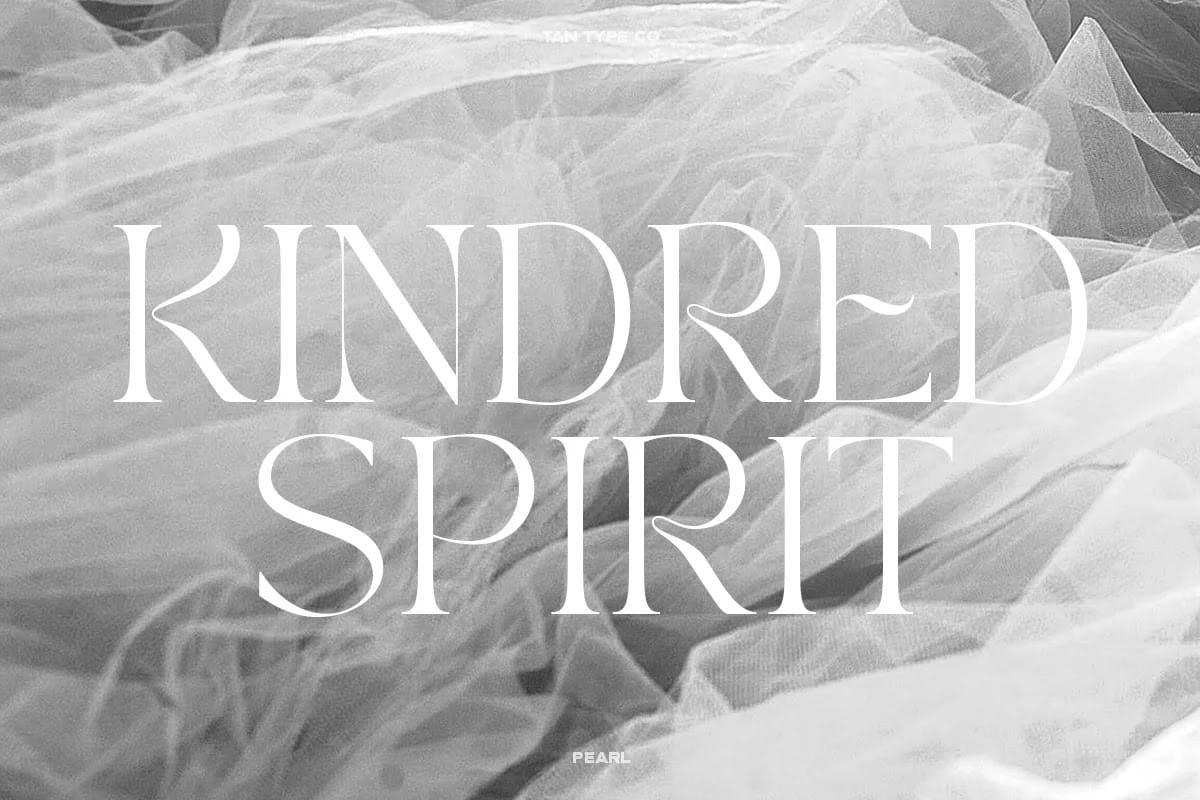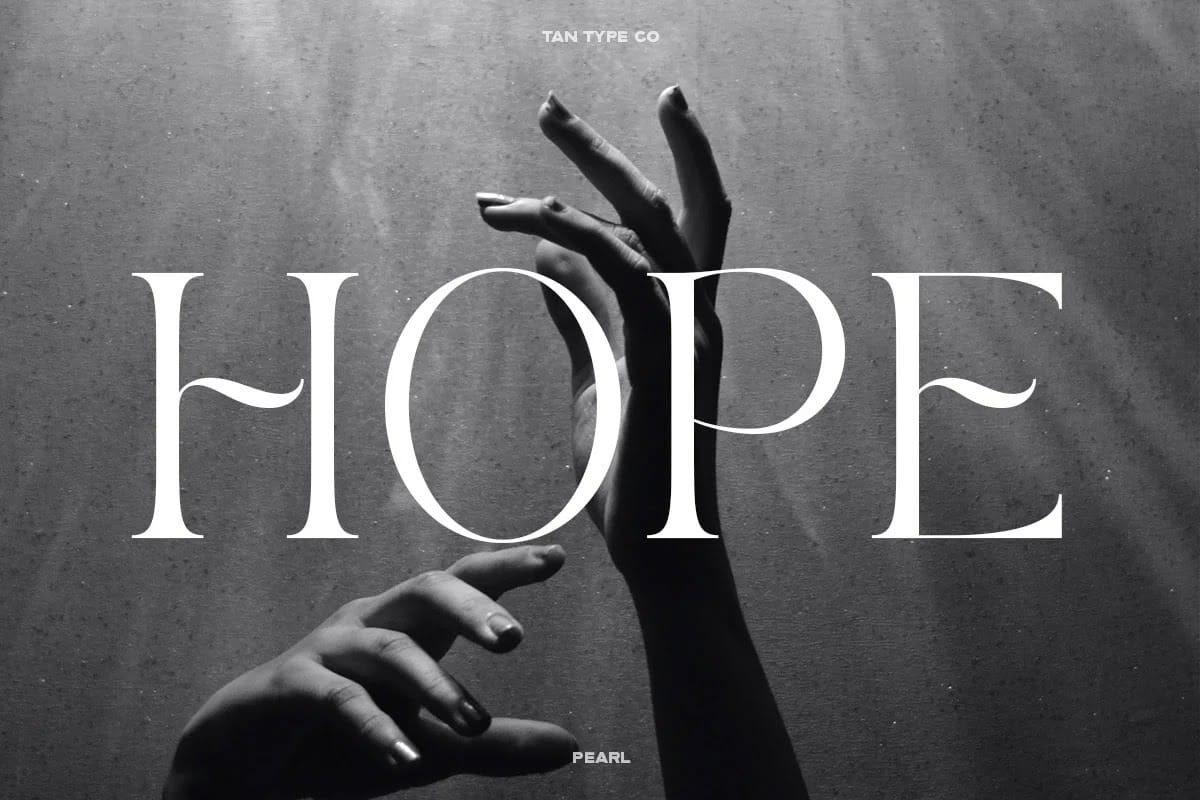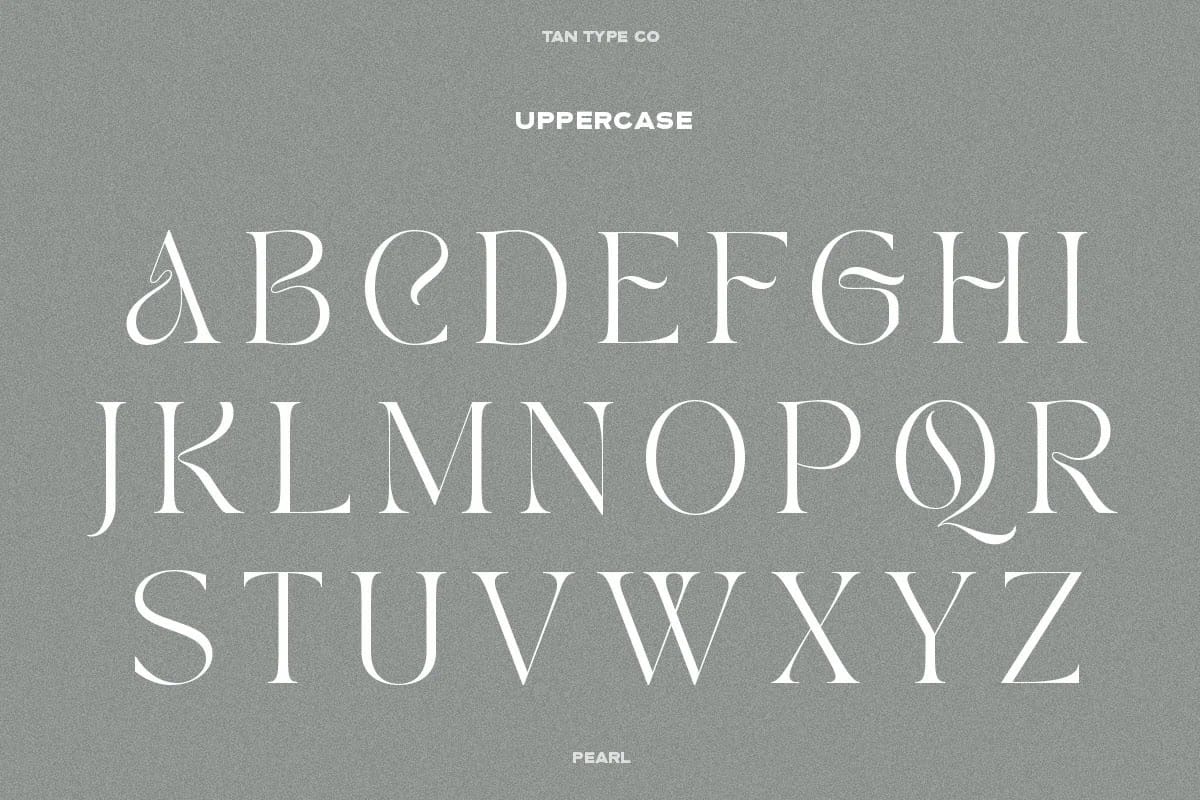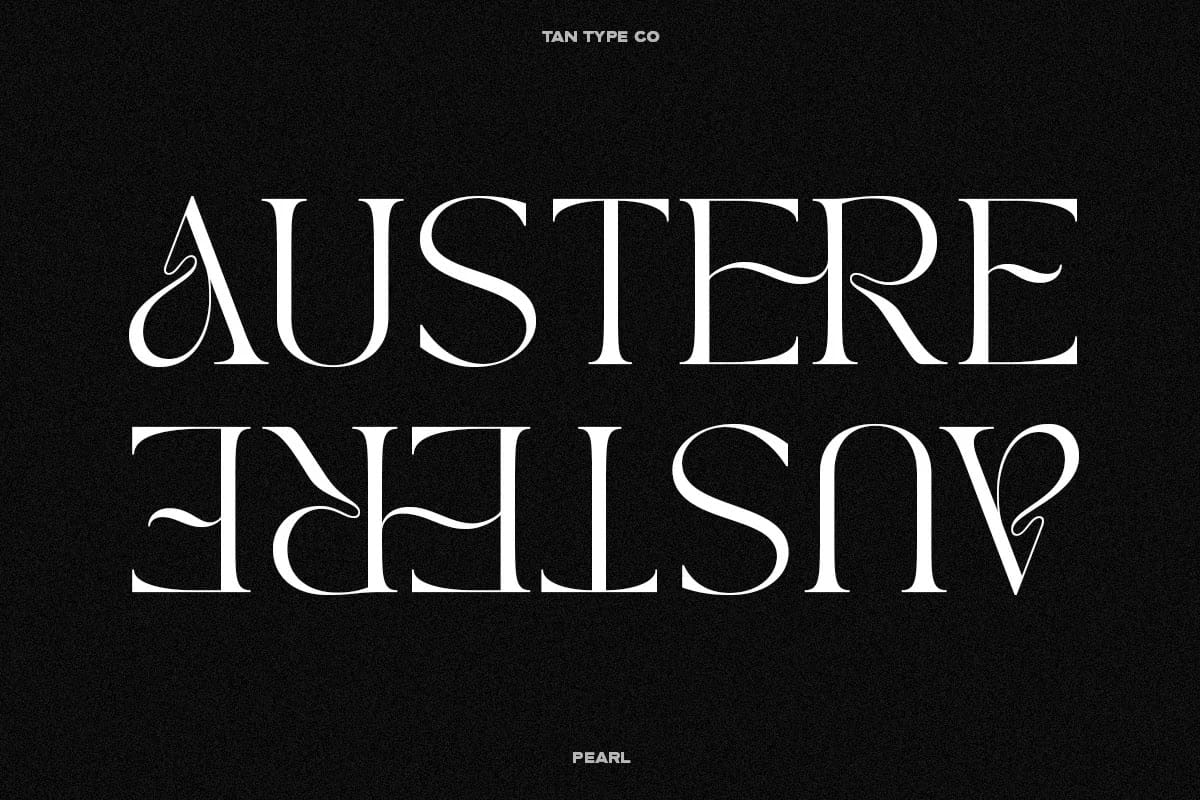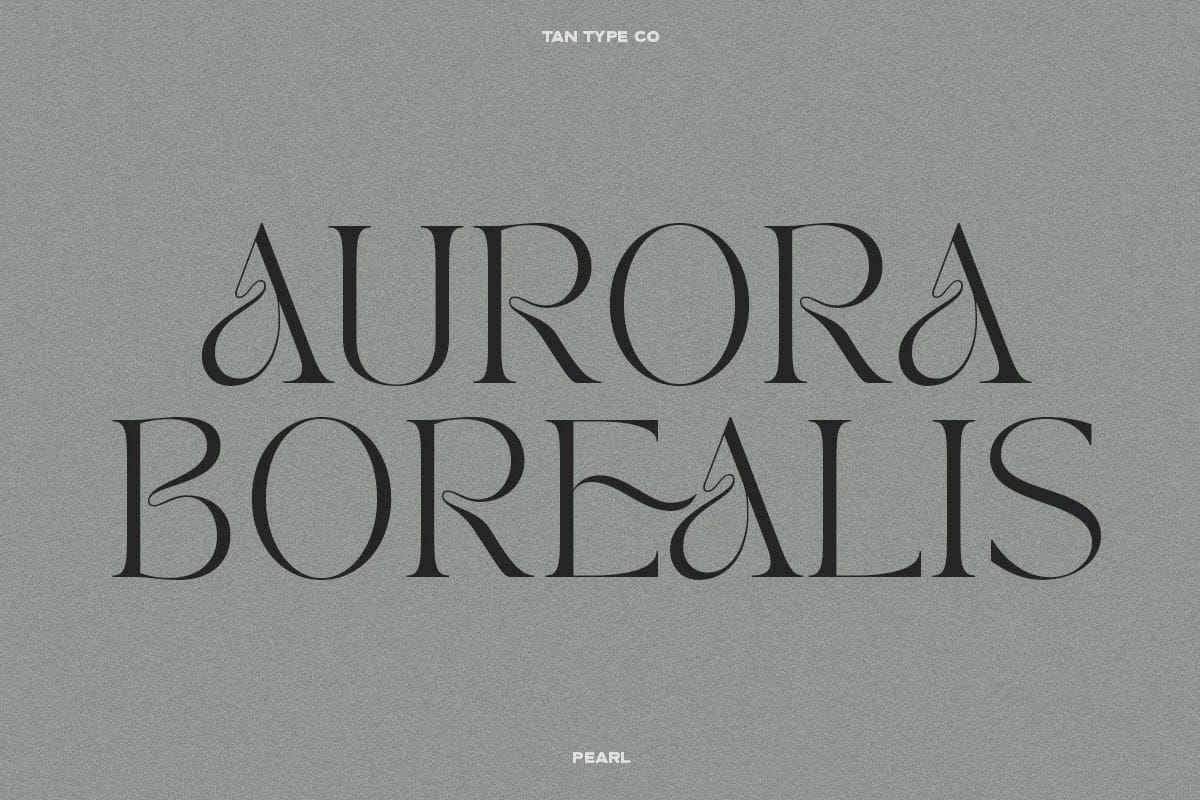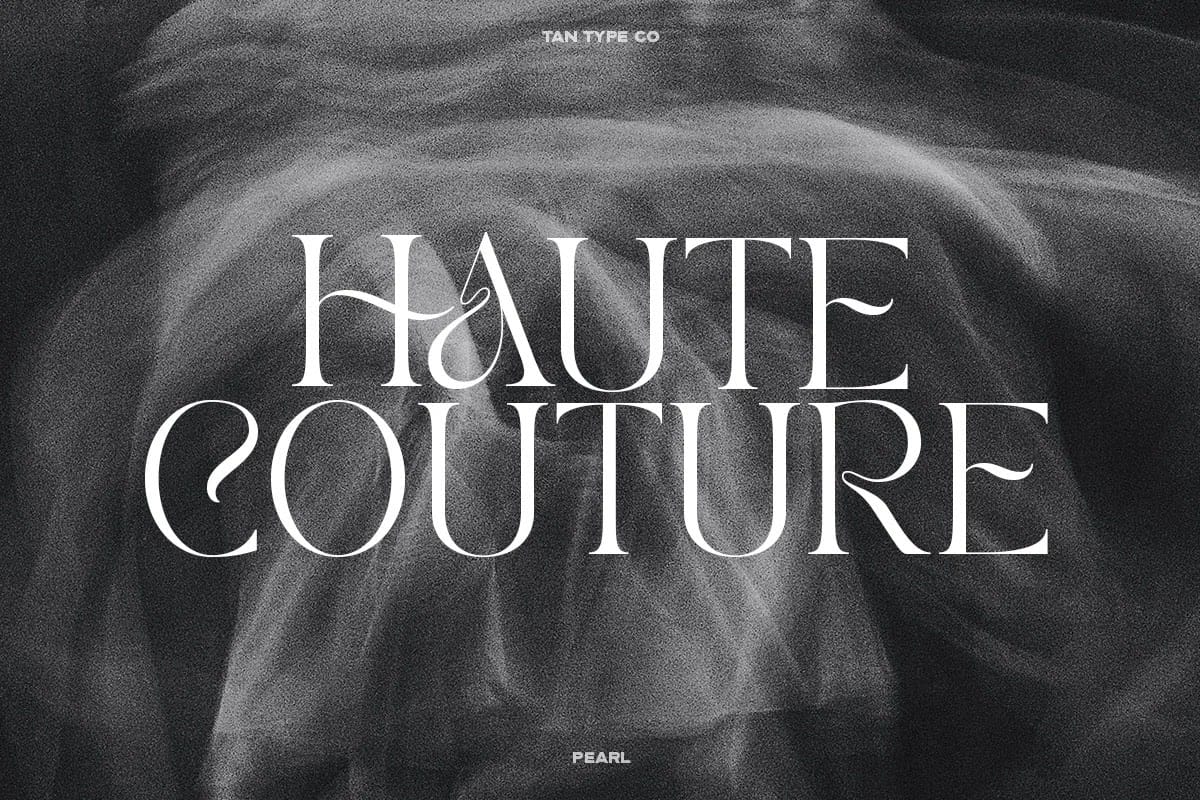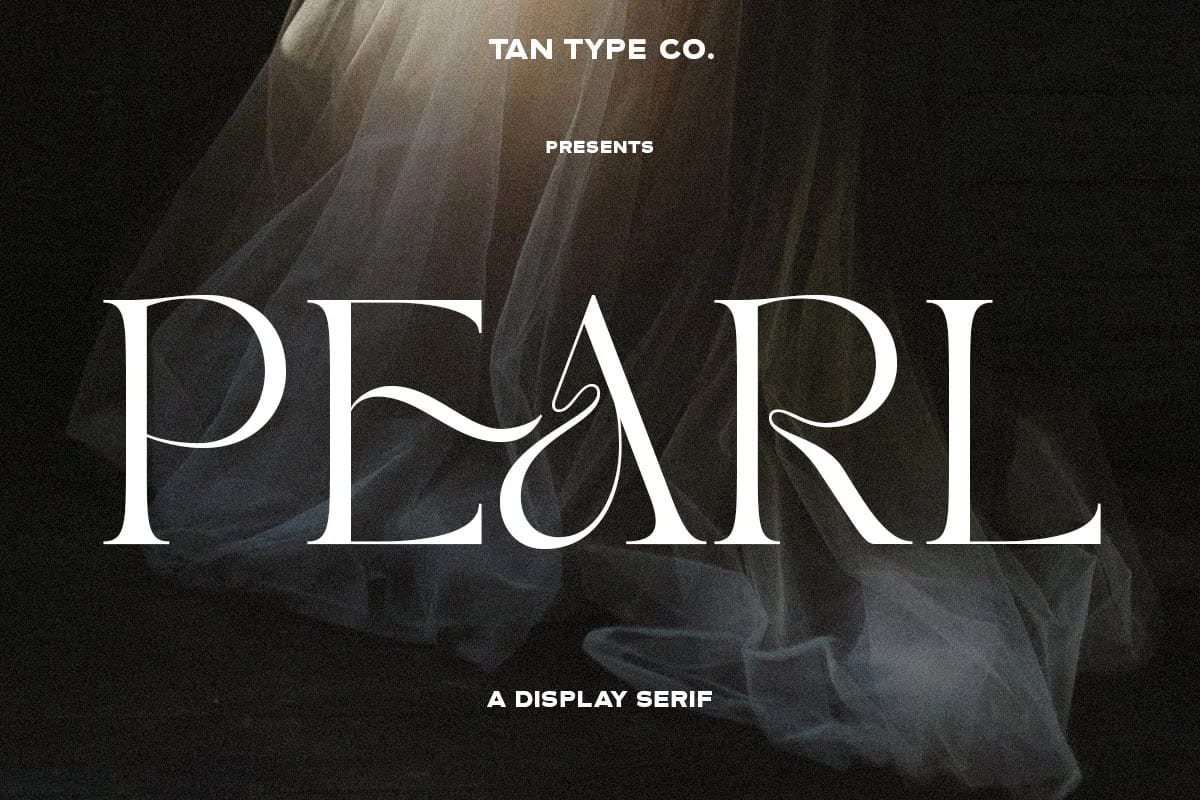
TAN – PEARL là một font serif vui tươi nhưng hiện đại. Với những đường cong tuyệt mỹ sẽ khiến bạn ấn tượng ngay từ cái nhìn đầu tiên. Hoàn hảo cho bất cứ điều gì mà sự sáng tạo của bạn mang lại cho bạn. 🙂
Đây là font chữ được sử dụng làm tiêu đề bài hát SÀI GÒN, HÔM NAY MƯA – JSOL & HOÀNG DUYÊN